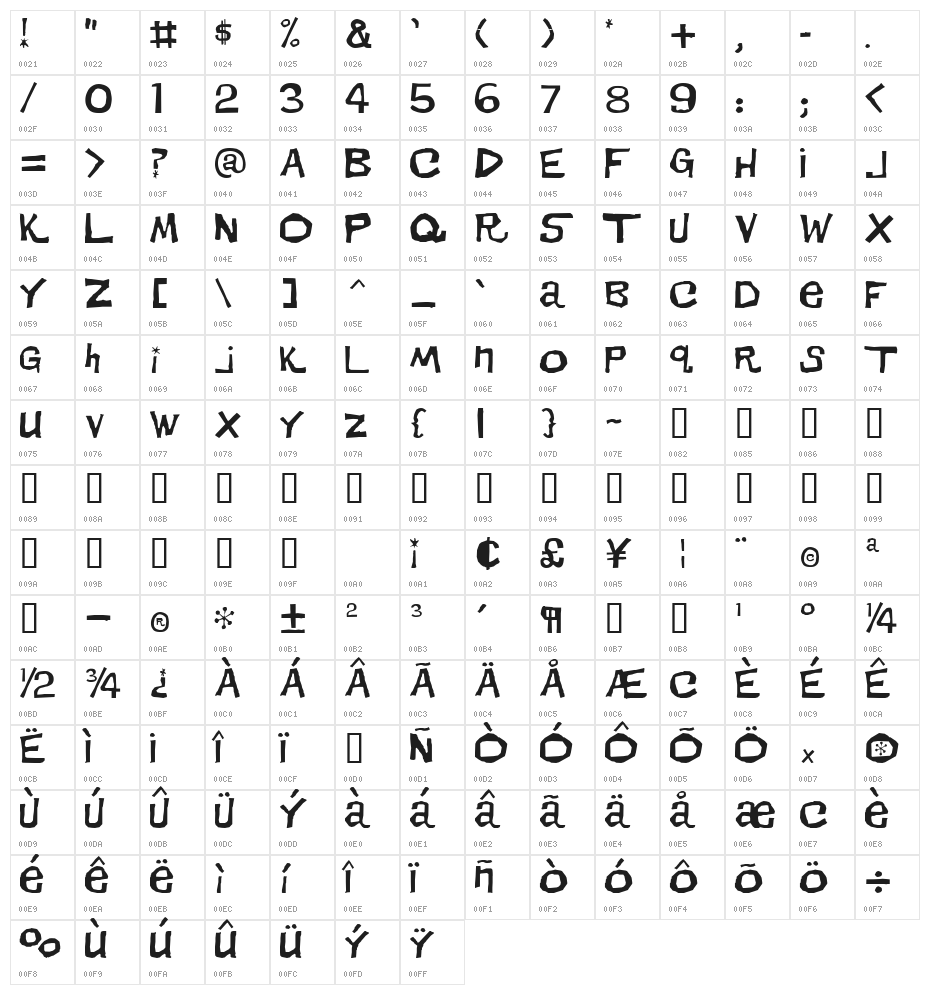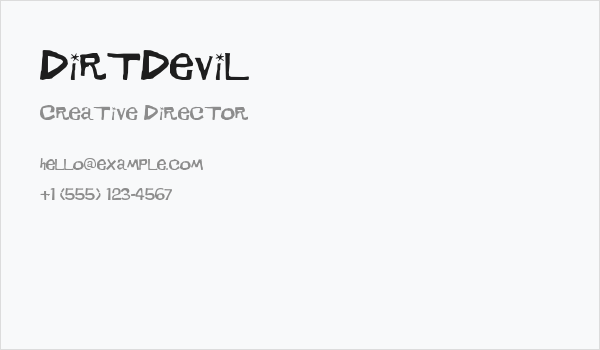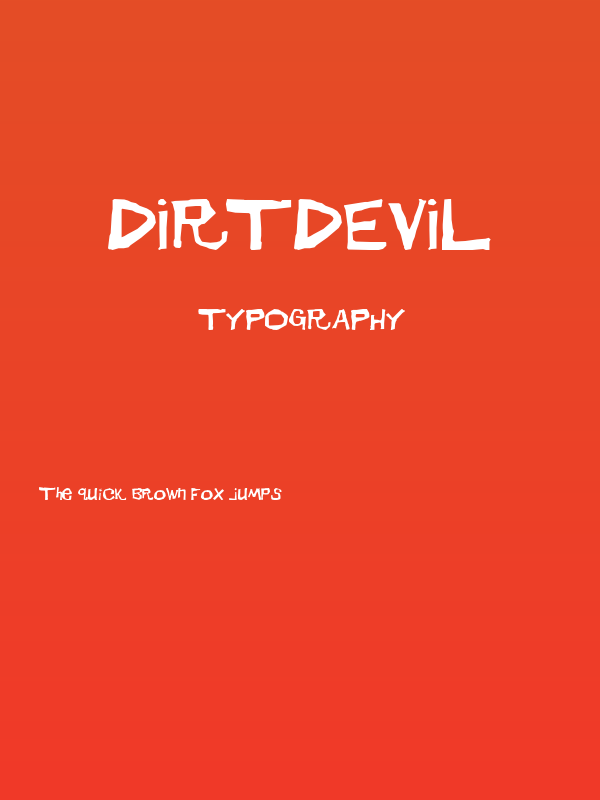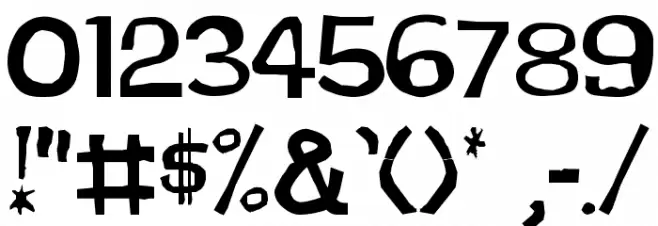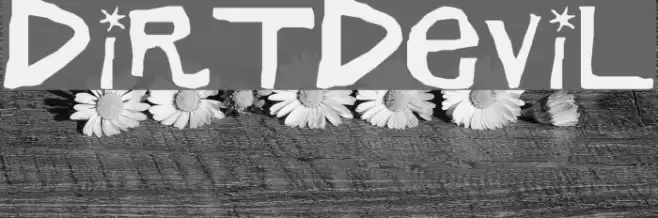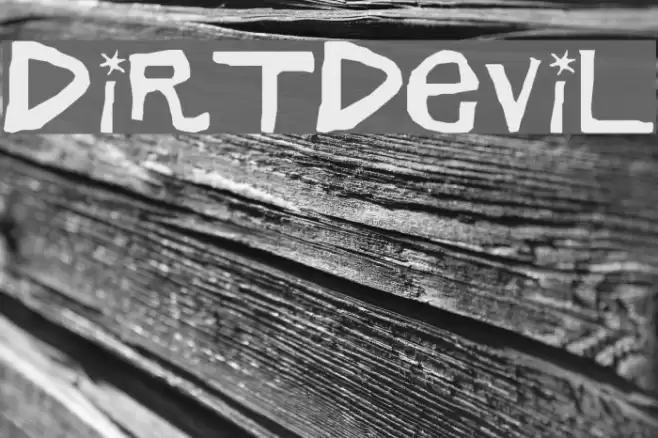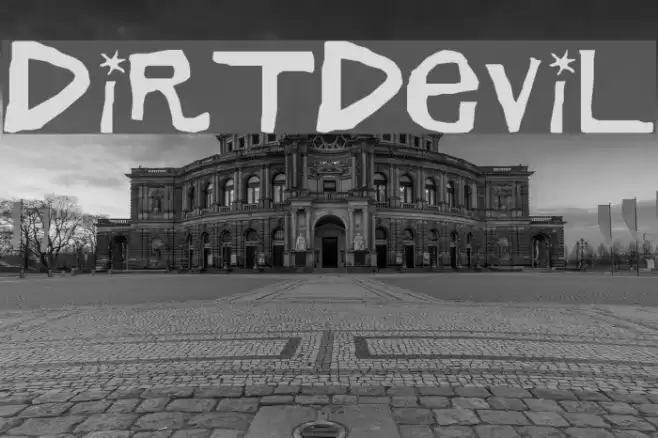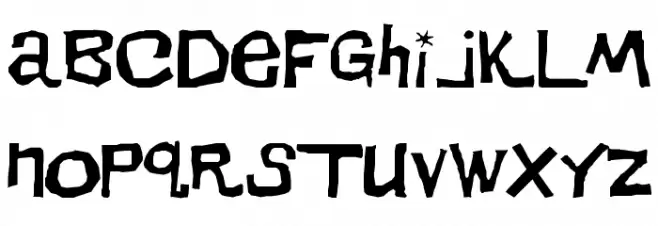
DirtDevil Font
Esta fonte inclui 207 caracteres. Clique em qualquer caractere para ver os detalhes.
| Projetos propostos | Ideal for street art-inspired designs, edgy branding, album covers, posters, and creative advertising campaigns. |